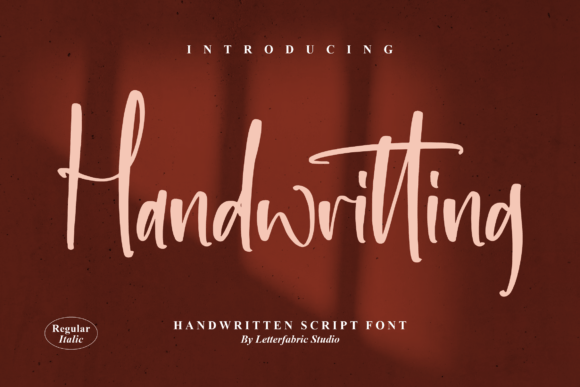
Handwritting
適切なデザイン要素を見つけるのは難しい場合がありますが、Handwrittingは作品を即座に引き立てる優れたコレクションを提供します。
POD(オンデマンド印刷)製品、結婚式の招待状、またはソーシャルメディアのグラフィックを作成している場合でも、Handwrittingは理想的です。